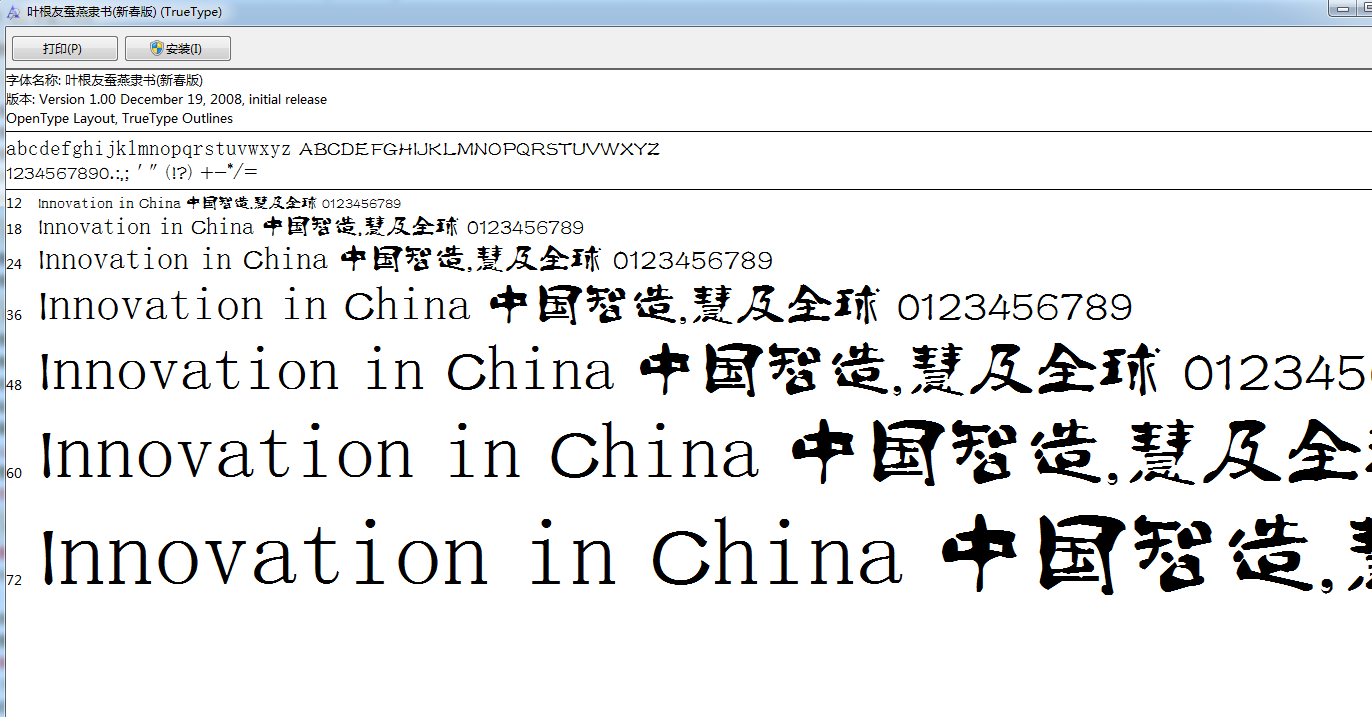
葉根友蠶燕隸書是一款具有隸書的傳統(tǒng)風(fēng)格和現(xiàn)代書法之結(jié)合體創(chuàng)新字體,賦予字體內(nèi)在的遒勁之美,圓潤(rùn)而富有質(zhì)感,特點(diǎn)鮮明,讓人看后過(guò)目不忘,為葉根友系列字體最受歡迎字型之一。將隸書的蠶頭燕尾之風(fēng)格包容于字里行間,用現(xiàn)代的創(chuàng)作思維去于古代書法對(duì)話,正所謂師古而不泥古,在葉根友認(rèn)為,所有書法創(chuàng)新也好,創(chuàng)作也罷,均是建立在古人的肩膀上去思考,但是不能一味的去模仿古人,而是要有自己的風(fēng)格特征,正如這款葉根友蠶燕隸書字體作品而言,每個(gè)字的起筆和運(yùn)筆都流露出一種書寫者當(dāng)時(shí)的真實(shí)心境,這款字體是在江蘇常州創(chuàng)作的,歷史四個(gè)月的書寫過(guò)程,每次寫完不滿意的一律扔掉,前后大約有些字寫了八到十次之多。